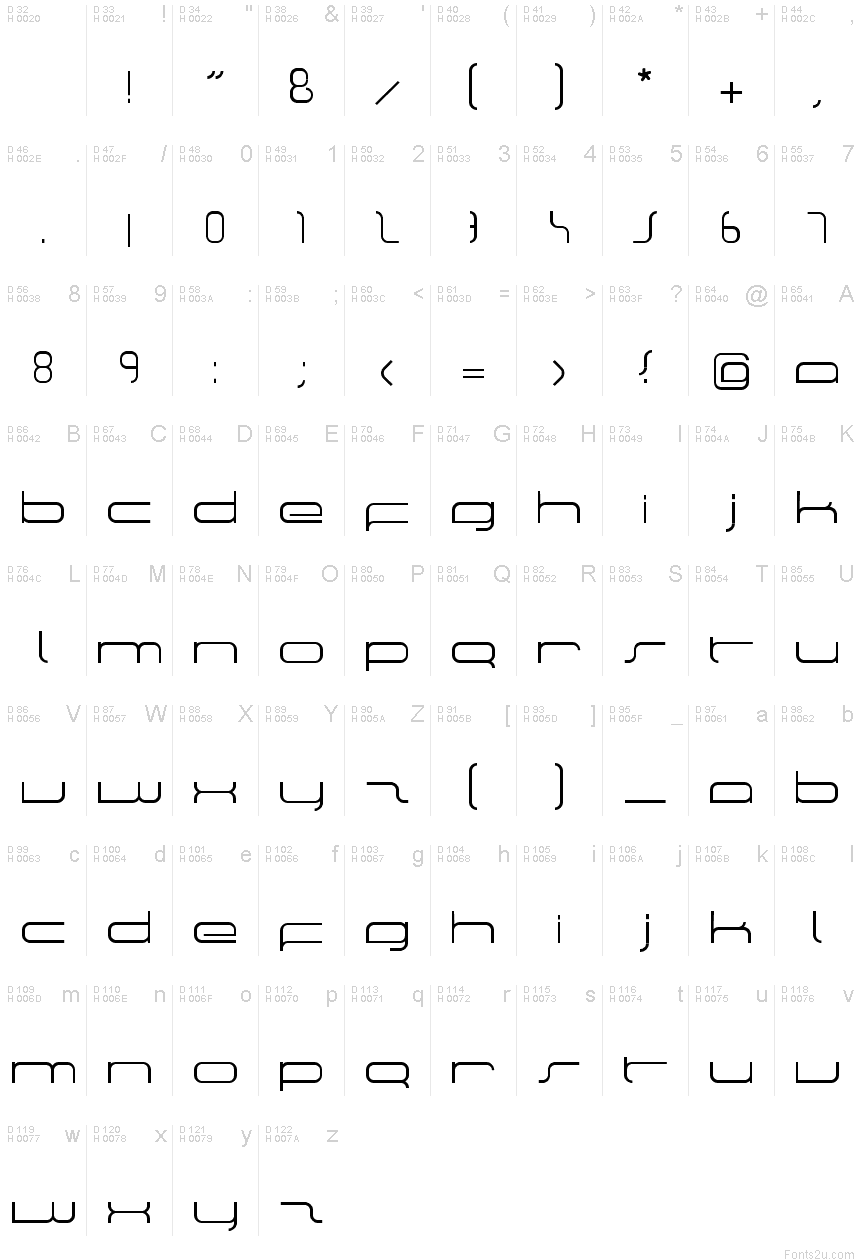
Manu Light to darmowy krój typu display o zaokrąglonych, geometrycznych kształtach i gładkiej linii o niskim kontraście, co sprawia, że znaki pozostają otwarte i przejrzyste. Miękkie narożniki i zwarty rytm nadają mu precyzyjną, a zarazem swobodną strukturę, która świetnie pasuje do czystych układów graficznych, nie sprawiając wrażenia sztywności.
Manu Light sprawdza się w projektach logo, krótkich hasłach brandingowych, tytułach na plakatach, opakowaniach i minimalistycznej grafice internetowej, ponieważ proste krzywe zachowują wyrazistość w większych rozmiarach. Ten darmowy font idealnie nadaje się również do akcentów w magazynach, nazw aplikacji czy podpisów redakcyjnych, gdzie wymagana jest kontrolowana, opływowa forma bez zbędnych ozdobników.